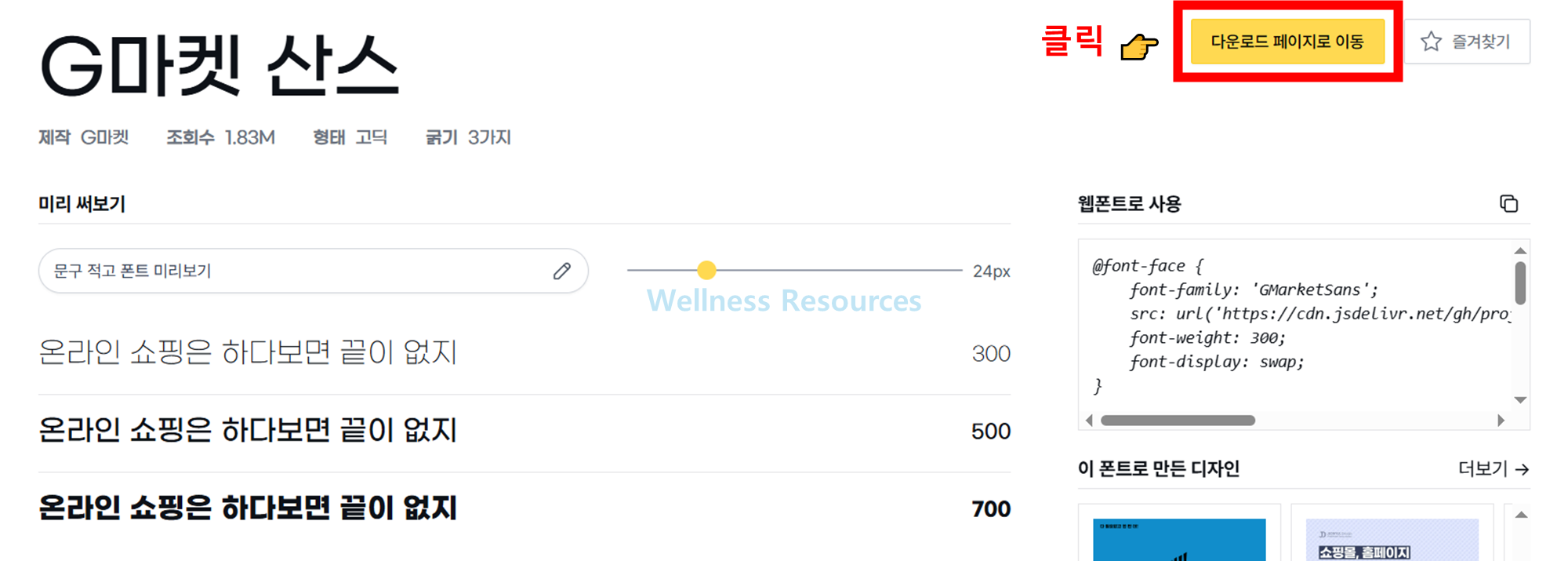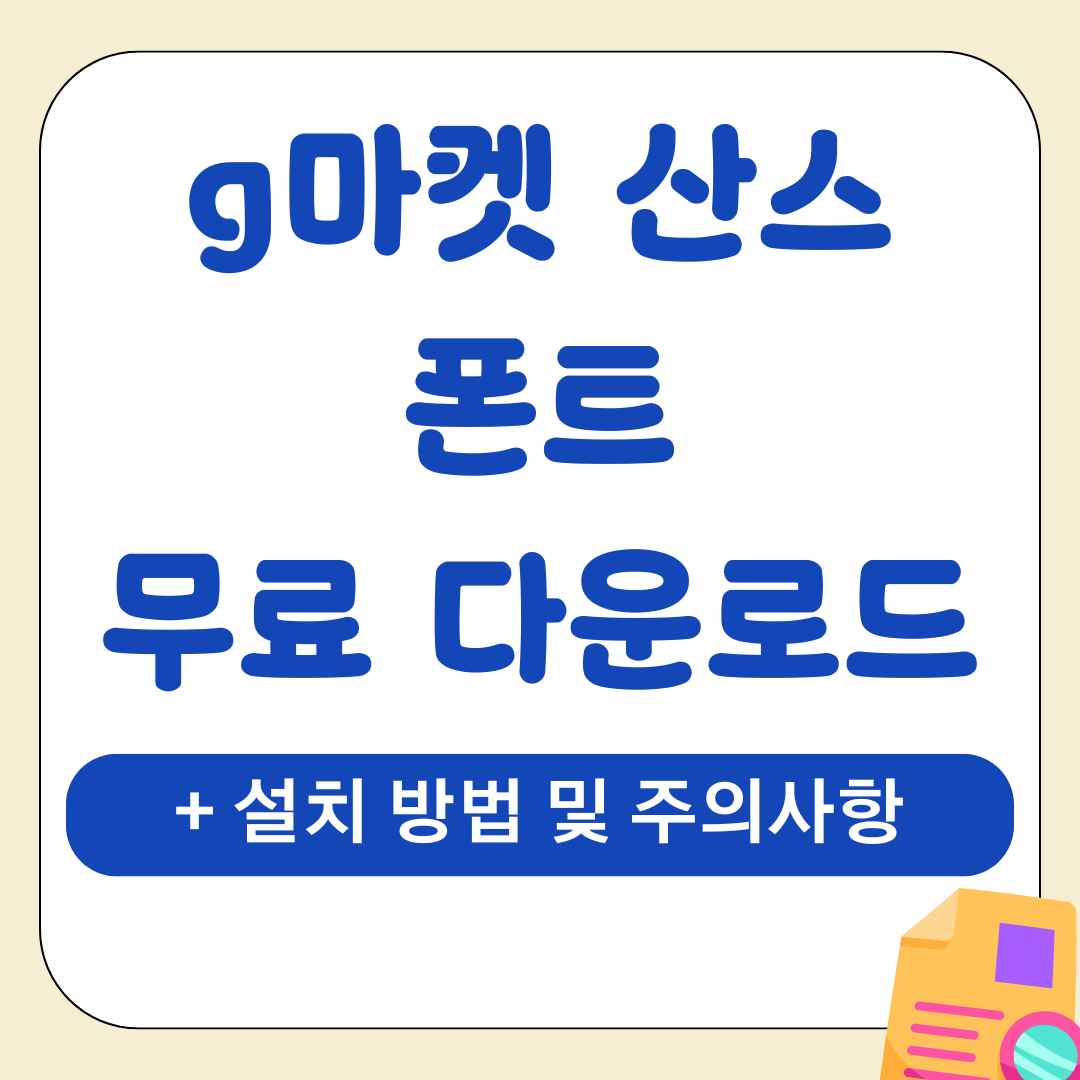
G마켓 산스 폰트는 가독성 높은 디자인과 상업적 무료 사용이 가능한 라이선스로 개인과 기업 모두 활용할 수 있는 인기 폰트입니다. 본문에서는 G마켓 산스 다운로드 경로, Windows·macOS 설치 및 삭제 방법, 저작권 범위와 주의사항까지 표로 정리해 안내하며 누구나 쉽게 이용 가능합니다.